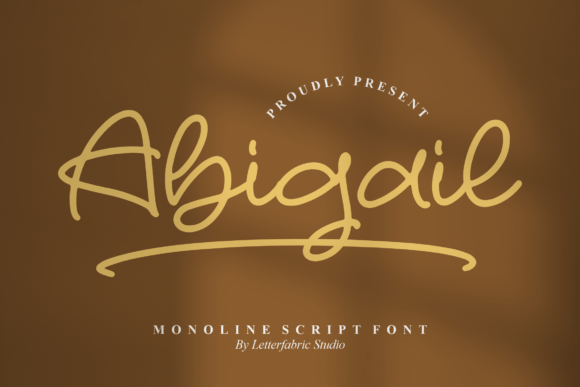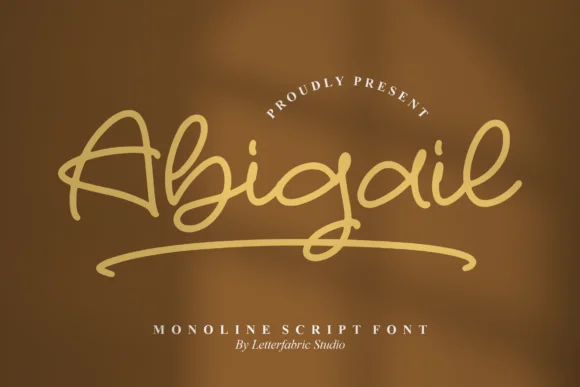
[Creativefabrica] Abigail Font (2022)
Abigail - монолитный фирменный шрифт со стильным рукописным начертанием, полным кривых, штрихов, линий и многого другого. Баланс в каждом слове поистине необычен!